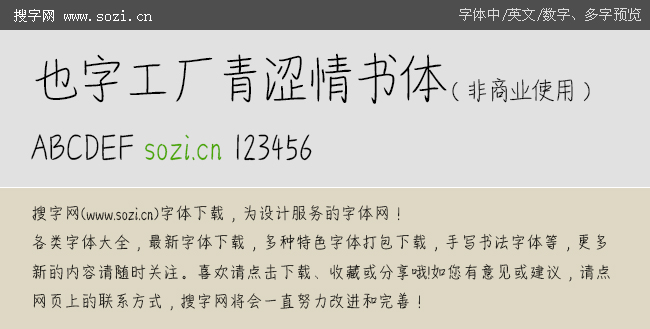
也字工廠青澀情書體
搜字網(wǎng)給大家提供一款也字工廠青澀情書體(非商業(yè)使用)中文字體下載,也字工廠青澀情書體是一款手寫書法字體,其字形俊秀、遒勁有力,優(yōu)雅中透出知性的氣息。文從字順,字形筆畫柔美俊秀、剛?cè)岵,結(jié)構(gòu)自然灑脫,充滿活力朝氣的青春氣息。適合應(yīng)用于書籍畫冊、海報、網(wǎng)頁設(shè)計等應(yīng)用(此字體為個人非商用版,商用可以聯(lián)系:官方網(wǎng)址:https://yefont.com/home,聯(lián)系方式:13798980448)。